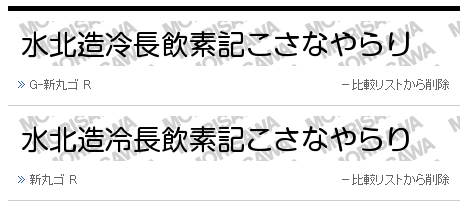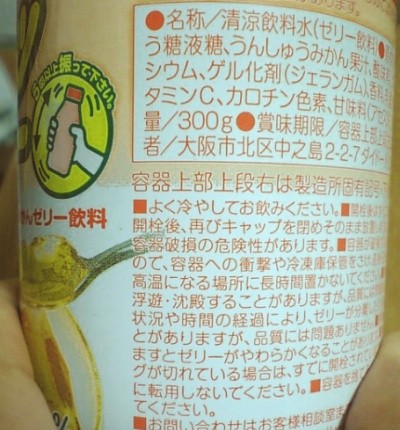
DyDo ぷるりんフルーツゼリー <みかん> のパッケージ。
新丸ゴ。どういう意図があるのか(あるいは無いのか)は知らないが、学参フォントが使われている。
普通の新丸ゴと字形を比較してみると、こんな感じ。
学参フォントは元の書体の字形を一部変えただけなのだが、一部変えただけなので逆にバランスが悪くなり、違和感が生まれているように思う。その字全体を一から作り直せば、学参用の字形であってももう少し違和感の無いものができると思うんだけど。まぁコストの問題ですかね。